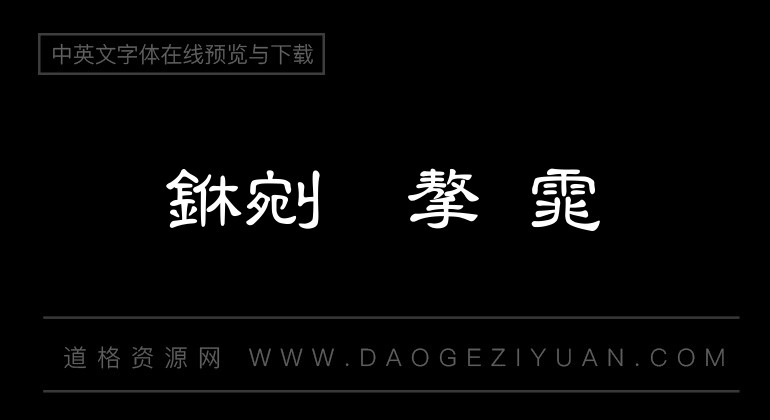
超研泽中粗隶是一款具有传统中国风格的字体,它具有细腻、流畅、清新的特点。字体的笔画较为粗犷,表现出稳重、古朴的气质,给人一种沉稳、淡雅的感觉,可以用于报刊、书籍、文化宣传物等,传达出浓厚的中国文化气息。文件名:ChaoYanZeZhongCuLiTi-1.ttf
超研泽中粗隶是一款非常不错的手写艺术字体,具有很好的视觉感,适合于文化类的宣传设计、商业类品牌的广告和产品包装设计以及个性化文字排版等较多场景。